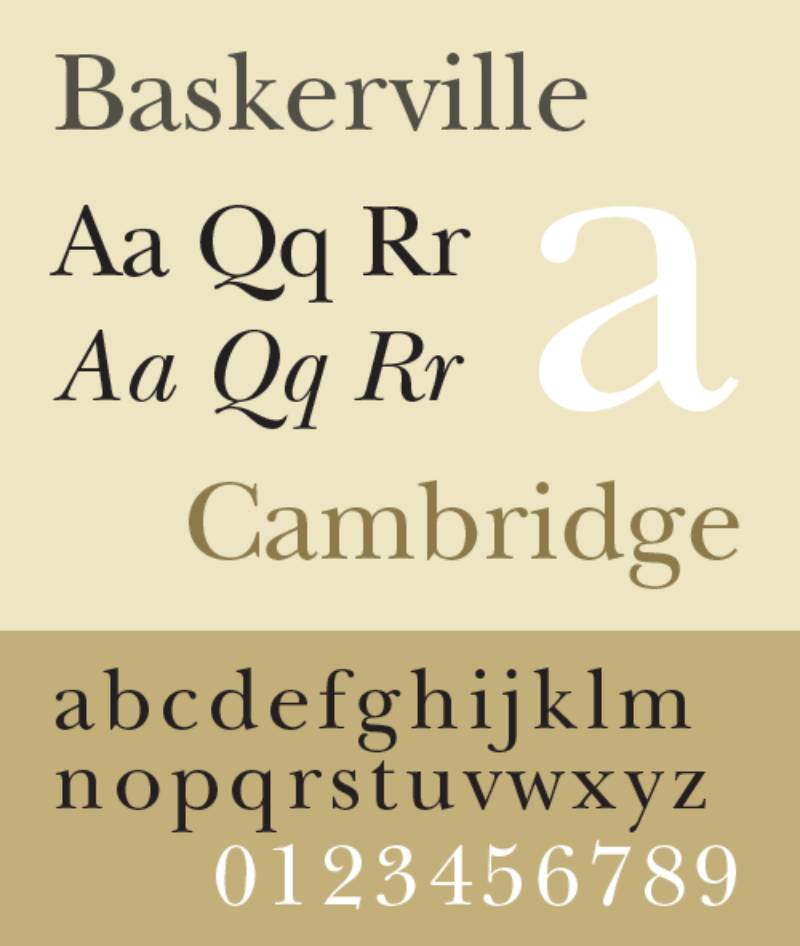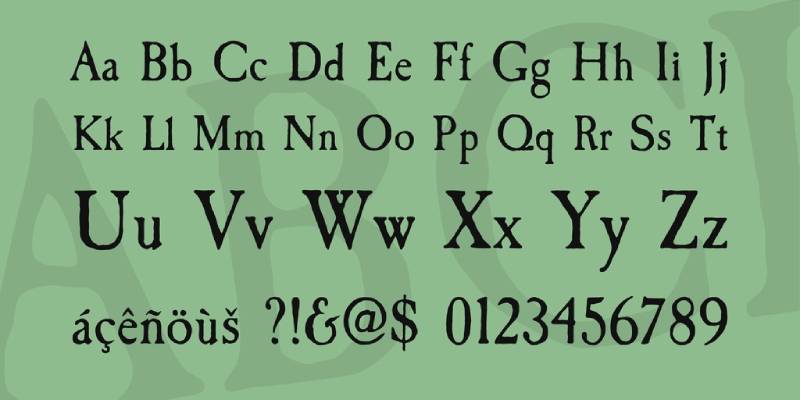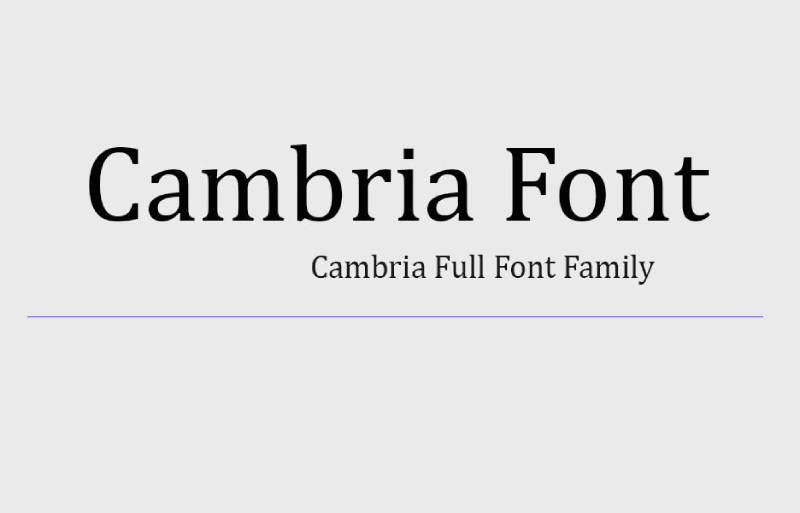
Stellen Sie sich vor, wie Sie sich in den Rhythmus des Verfassens Ihres akademischen Meisterwerks einfinden – die Worte fließen, die Ideen klingen, doch alles hängt davon ab, wie Ihre Prosa das Auge des Lesers trifft.
Ihnen ist bewusst, dass die besten Schriftarten für wissenschaftliche Arbeiten nicht nur leise zum Intellekt sprechen; sie rufen dem kritischen Betrachter in jedem Gutachter zu.
Hier entfaltet sich eine Erzählung, nicht nur über Typografie, sondern auch über den stillen Botschafter Ihres akademischen Epos.
Bei der Erstellung dieses Leitfadens habe ich meinen Fokus auf einen entscheidenden, oft unterschätzten Akteur in der akademischen Arena gerichtet: die Auswahl der Schriftart.
Navigieren Sie durch diese Straßenkarte und entdecken Sie einen Schatz an lesbaren Schriftarten und Formatierungstipps, die sicherstellen, dass Ihre Arbeit ein Markenzeichen von Klarheit und Professionalität ist.
Erfahren Sie Einsichten – von der verehrten Times New Roman bis zur dezenten Eleganz von Arial – gepaart mit unverzichtbaren Formatierungstipps, die über die bloße Einhaltung von Universitätsrichtlinien hinausgehen.
Tauchen Sie tief ein und entsperren Sie am Ende des Artikels ein Dossier mit weisen Ratschlägen, die Ihre Dokumente in der genauen Welt der akademischen Prüfung hervorheben.
Hier geht es darum, dass Typografie nicht nur als Gefäß dient, sondern als Ihr Verbündeter im wissenschaftlichen Diskurs.
Die besten Schriftarten für wissenschaftliche Arbeiten
| Schriftart | Serif/Sans-Serif | Lesbarkeit | Verwendung | Anmerkungen |
|---|---|---|---|---|
| Times New Roman | Serif | Hoch | Formelle Arbeiten, Zeitschriften | Standardmäßig und weit akzeptiert |
| Arial | Sans-serif | Hoch | Präsentationen, weniger formell | Klar und modern |
| Calibri | Sans-serif | Hoch | Allgemeine wissenschaftliche Arbeit | Standard in Microsoft Word, gut ausbalanciert |
| Helvetica | Sans-serif | Hoch | Professionelle Arbeiten | Klassisch und neutral, kann weniger formell sein |
| Garamond | Serif | Mittel | Lange Texte, Bücher | Altmodischer Stil, gibt ein klassisches Aussehen |
| Palatino | Serif | Hoch | Geisteswissenschaftliche Arbeiten | Elegant und leicht lesbar |
| Baskerville | Serif | Mittel | Formelle und traditionelle Werke | Professionell und autoritär |
| Caslon | Serif | Hoch | Akademische Zeitschriften | Traditionell und dauerhafte Lesbarkeit |
| Georgia | Serif | Hoch | Online und gedruckter Text | Speziell für Bildschirmlesbarkeit entwickelt |
| Cambria | Serif | Hoch | Elektronisch und gedruckte Arbeiten | Entwickelt für Bildschirmlesbarkeit und Ausgabe |
Traditionelle Auswahlmöglichkeiten und ihre Grenzen
Times New Roman: Allgegenwärtigkeit und Lesbarkeit vs. Übergebrauch
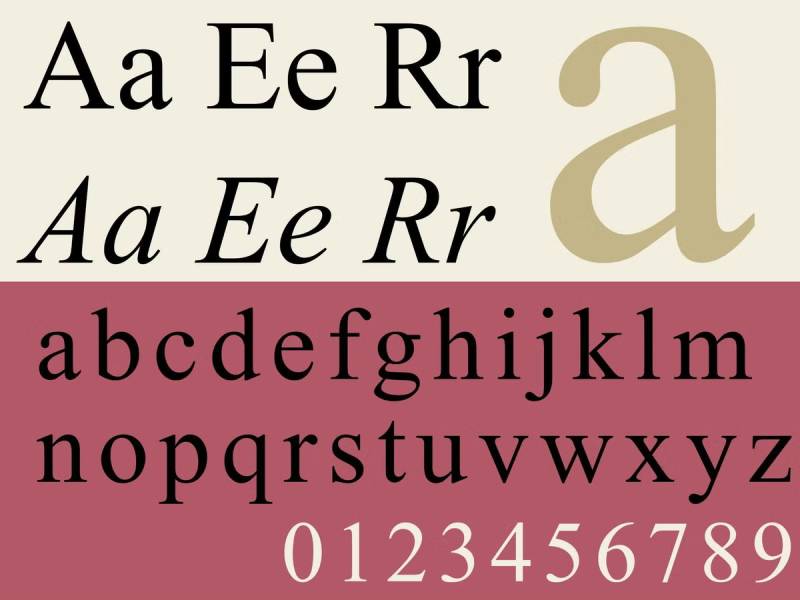
Ah, Times New Roman, der Großvater der akademischen Schriftarten. Es ist wie dieser zuverlässige alte Freund, immer da, immer lesbar. Aber hier ist die Sache – es ist fast zu bekannt. Es ist überall, richtig? Nichtsdestotrotz ist seine Lesbarkeit unbestreitbar, was es zu einer soliden Wahl für Ihre Arbeiten macht.
Arial: Lesbarkeit in verschiedenen Textblöcken
Weiter mit Arial. Denken Sie daran als den luftigen, modernen Cousin von Times New Roman. Es ist unkompliziert, praktisch und super lesbar in verschiedenen Textgrößen. Eine sichere Wahl für digitale Dokumente, besonders wenn Sie diesen sauberen, zeitgenössischen Look anstreben.
Calibri: Bildschirmlesbarkeit vs. Einschränkungen im gedruckten Text
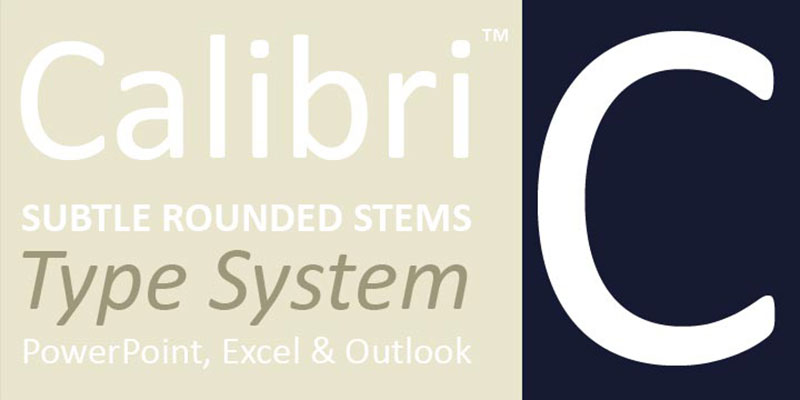
Calibri tritt als der Neue in der Stadt auf. Es ist ein Champion auf Bildschirmen, dank seiner klaren und runden Zeichen. Aber Vorsicht, im Druck kann es etwas von diesem Charme verlieren. Es kommt ganz darauf an, wo Ihr Papier gelesen wird.
Helvetica: Häufige Nutzung und einfache Lesbarkeit, geeignet für sowohl Druck als auch Bildschirm
Helvetica ist wie der coole, vielseitige Künstler unter den Schriftarten. Es ist überall – von U-Bahn-Schildern bis hin zu Tech-Marken. Und das aus gutem Grund! Es ist unglaublich leicht auf jeder Plattform zu lesen. Eine solide Wahl, wenn Sie möchten, dass Ihre akademische Arbeit mühelos lesbar ist.
Garamond: Historische Bedeutung und Eignung für lange Prosatexte
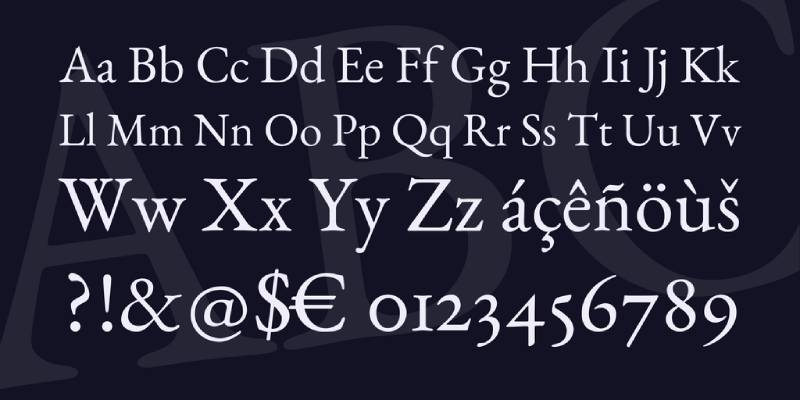
Garamond führt Sie weit zurück. Es hat diese altmodische, verfeinerte Atmosphäre. Perfekt für längere Stücke dank seines eleganten und klassischen Designs. Es ist wie das Tragen einer Vintage-Jacke – stilvoll und doch zeitlos.
Palatino: Eleganz und Lesbarkeit, gut für formelle akademische Arbeiten
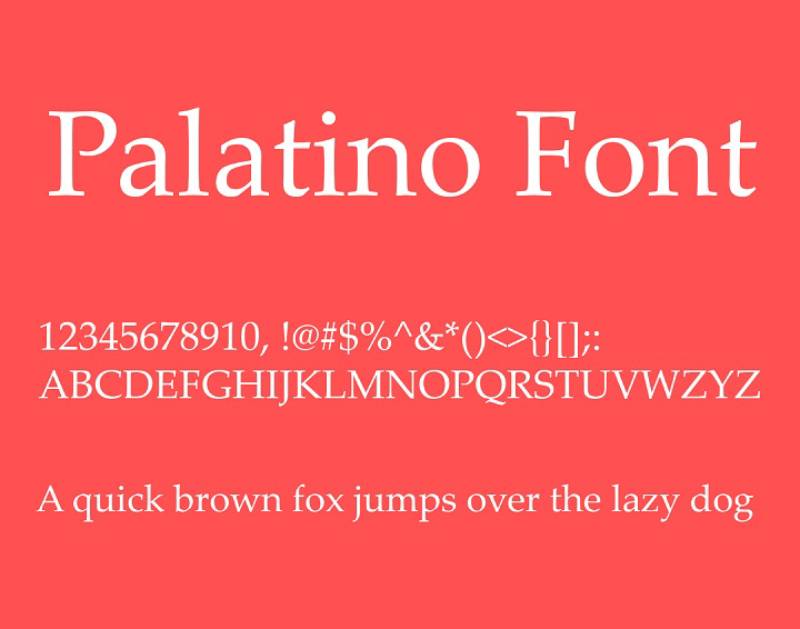
Schließlich Palatino. Stellen Sie sich eine große, alte Bibliothek vor – das ist Palatino. Es bringt einen Hauch von Eleganz, ohne die Lesbarkeit zu opfern. Ideal, wenn Sie Ihrem Werk eine Spur von Formalität verleihen möchten.
Serif vs. Sans-Serif-Schriften
Überlegungen zur Lesbarkeit und Formalität
Nun, die ewige Debatte: Serif oder Sans-Serif? Serifenschriften, wie Times New Roman und Garamond, bringen ein formelles, traditionelles Flair mit sich. Sie sind oft angenehmer für lange Lesezeiten. Sans-Serif-Schriften, wie Arial und Helvetica, bieten ein saubereres, moderneres Aussehen. Perfekt für kürzere Texte oder digitale Plattformen.